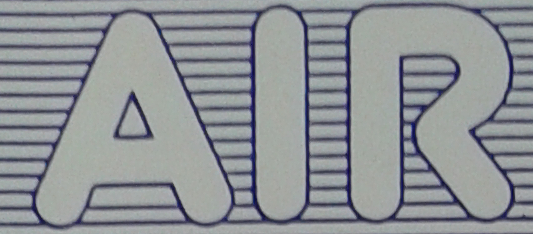
Schrift eines Industrieproduktes gesucht
mein Auftraggeber möchte dass ich ein Produktlogo digitalisiere. Mir liegt nur eine ältere Produktbeschreibung (ca. 1990)
in Printausgabe vor. Der damalige Ersteller dieses Logos ist nicht mehr auffindbar. Die bisherigen Versuche eine Schriftart zu finden die dem Logo gleichkommt schlugen fehl. Es handelt sich um ein Produkt welches sich zur Zeit noch nicht im Internet wieder findet und wiederbelebt werden soll.
Vielleicht kann mir hier jemand eine Hilfestellung geben um welche Schriftart es sich handelt. Es könnte auch gut möglich sein
dass es eine selbsterstellte Schrift ist.
Im Anhang lege ich das abfotografierte Logo bei. (Es handelt sich um einen Teil des Logos).
Rein zeitlich spricht einiges dafür, dass der damalige Grafiker diese Buchstaben von Hand gezeichnet hat. Und es spricht eigentlich auch nichts dagegen, diese nun digital anzuzeichnen, statt ewige nach einer geeigneten Satzschrift zu suchen ;-) sind ja nur drei Buchstaben und die Formen sind auch nicht grad komplex ;-)